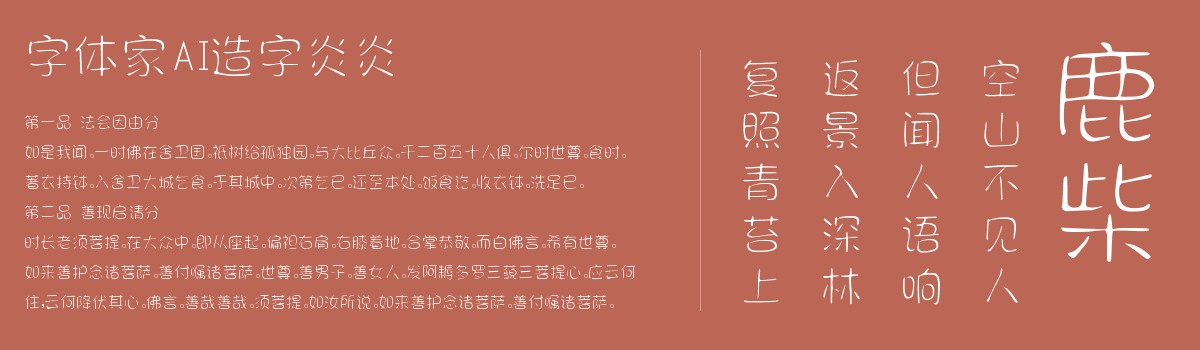
字体家AI造字炎炎
字体家AI造字炎炎是一款由字体家AI神笔造字生成的艺术字体,整体结构方正端庄,笔画粗细均匀,线条刚劲中带着柔和的圆角处理。横画平直稳重,竖画挺拔有力,转角处圆润过渡,无尖锐棱角。笔画末端利落干净,无多余装饰,重心平稳居中,部件比例协调均衡。整体兼具力量感与温和气质,刚硬线条显沉稳,圆角转角添亲和,给人可靠又不失柔润的美感。适合用于一些广告标题、平面文案、海报标题、网页广告用字的编辑。